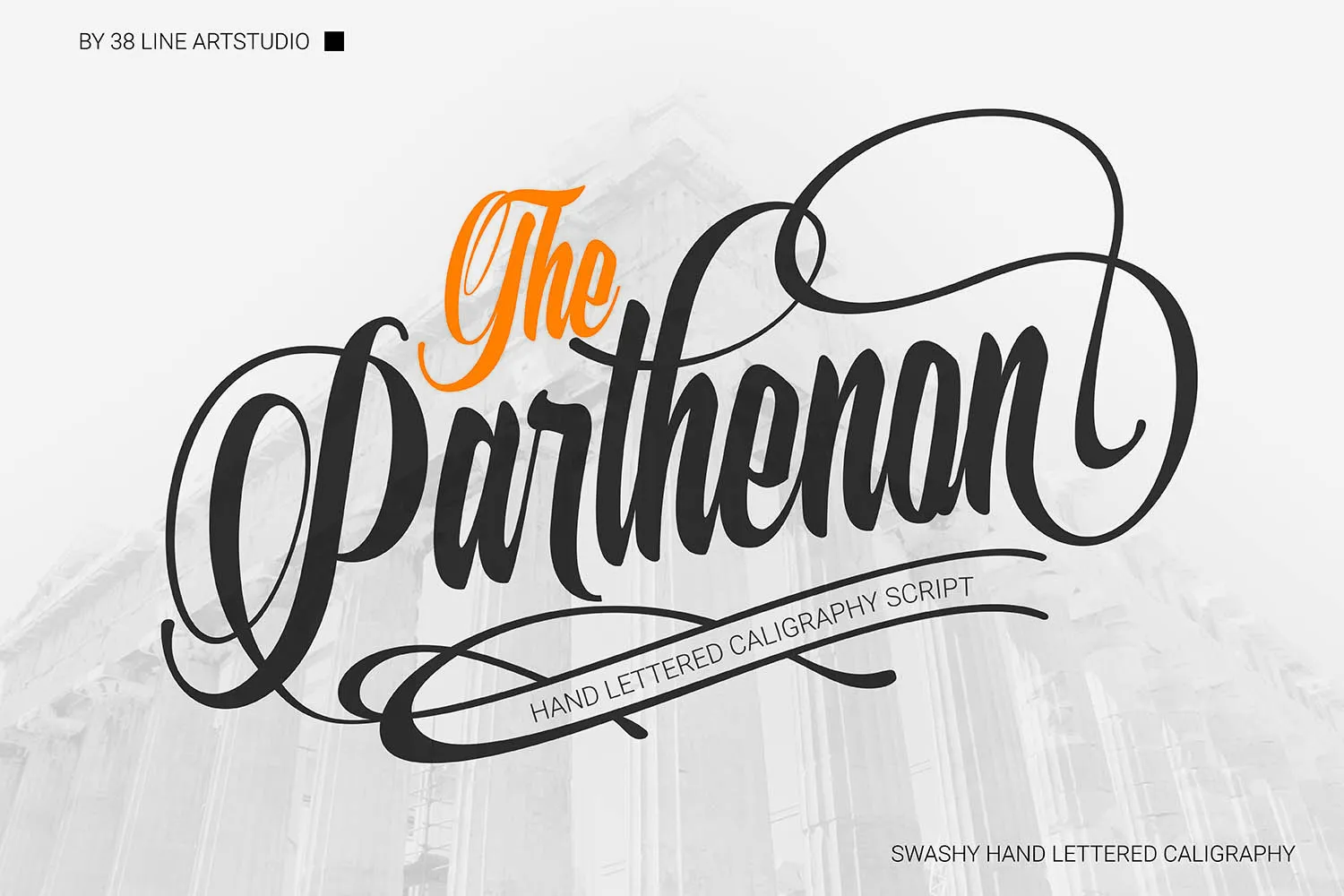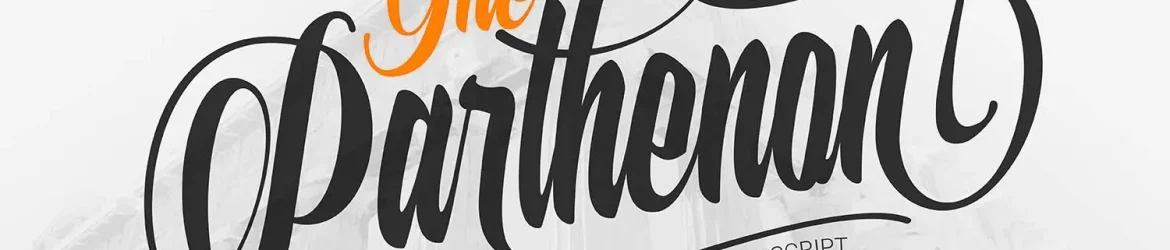
A fonte “The Parthenon Script Font” é uma escolha perfeita para quem busca adicionar um toque especial à sua identidade visual. Ela é inspirada na caligrafia grega do famoso templo de Atenas, o Parthenon. Esta fonte é uma obra de arte em si, uma caligrafia elaborada e meticulosa que permite aos designers criarem trabalhos de letra única e divertidos. “O Parthenon” oferece 6 a 7 alternativas de letras, permitindo inúmeras possibilidades para criar estilos de letra impressionantes. As alternativas permitem que você misture e match diferentes opções de cada letra para criar designs únicos e atraentes, capazes de captar o olhar do espectador de todos os ângulos. Engane seu público com um design elegante e único, a cada obra que cria. Com “The Parthenon Script Font”, você não apenas acrescenta personalidade à sua marca, mas também adorna suas produções com uma paleta vibrante de possibilidades criativas. Este é o ideal para designers apaixonados por criar designs impecáveis e trabalhos gráficos que fazem a diferença.